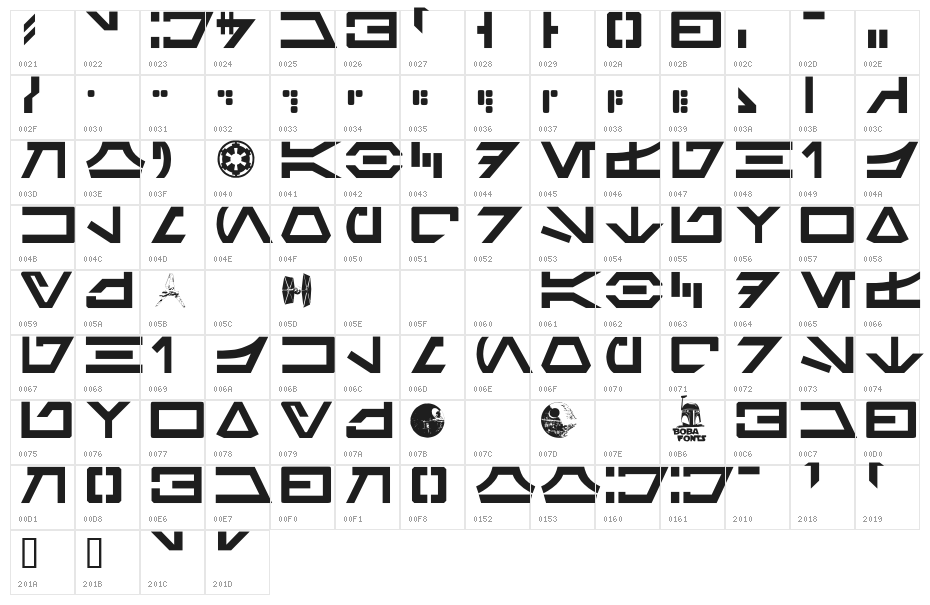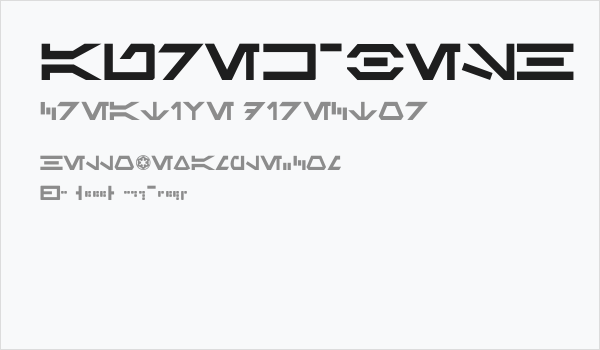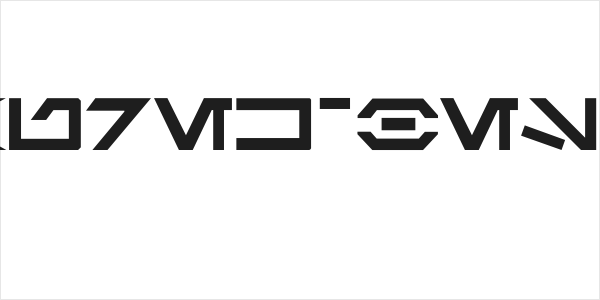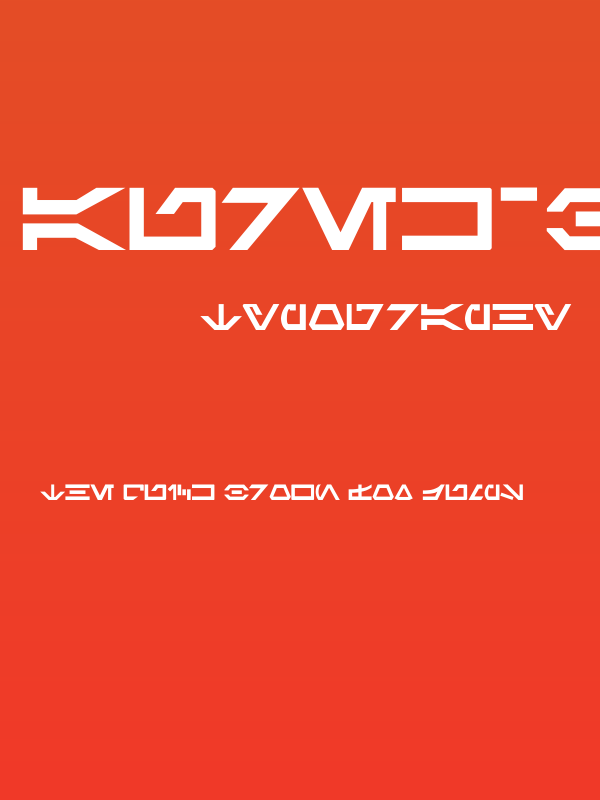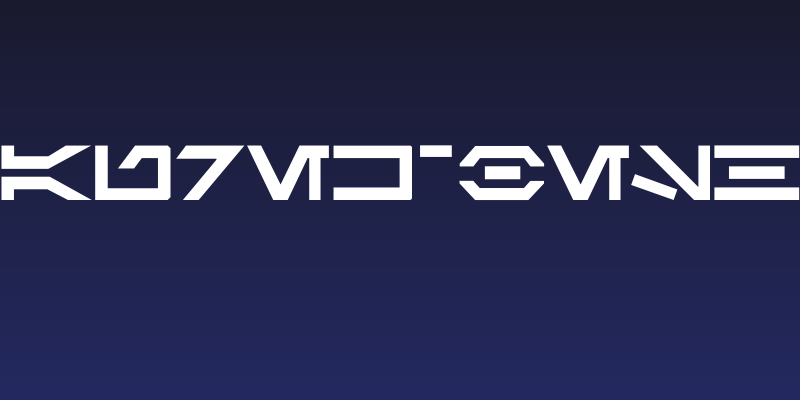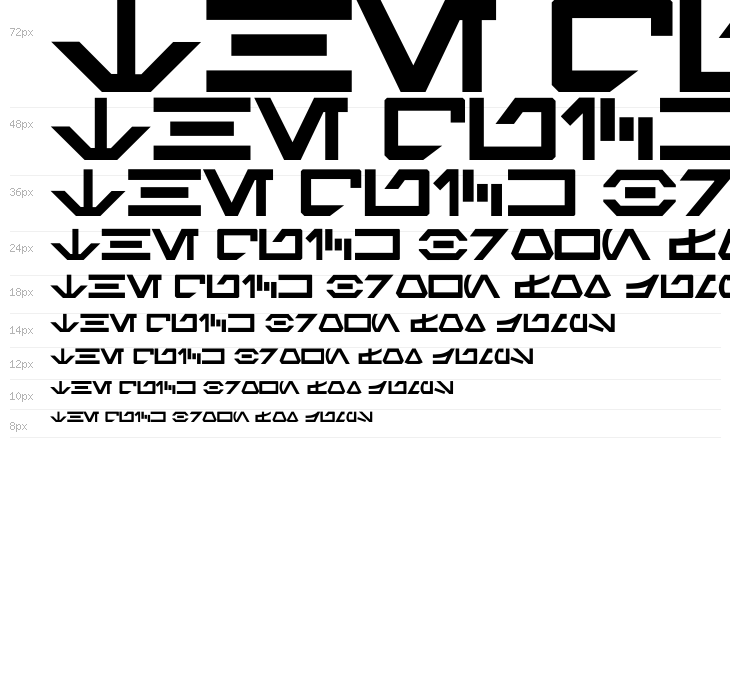
Aurek-Besh Font
| Stile generale | Futuristic |
| Caso d'uso | Logos, Posters, Themed Events |
| Progetti proposti | Ideal for science fiction themed projects, fan art, themed events, or any creative work that requires an extraterrestrial or futuristic feel. |